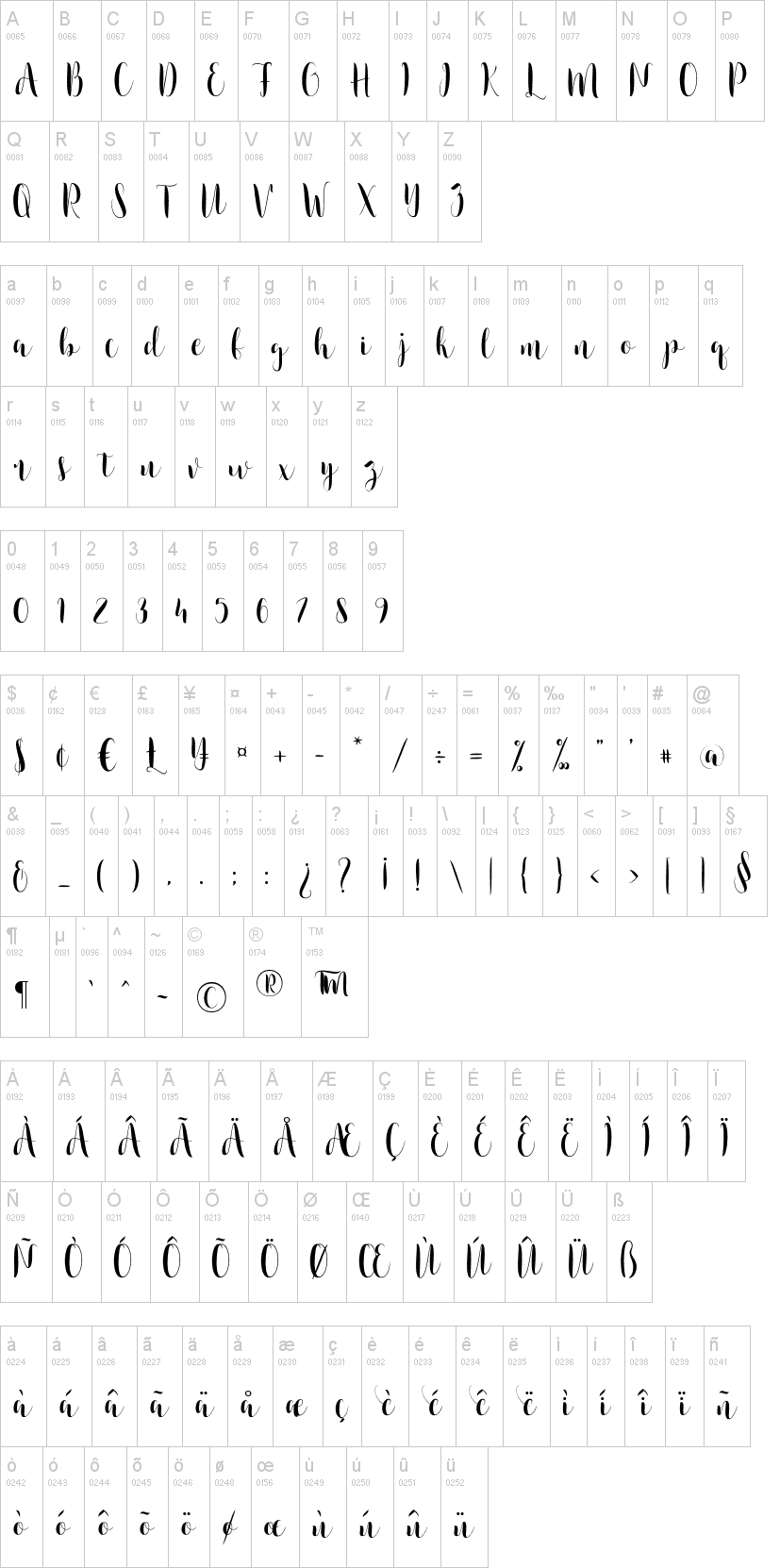
Camsia 字体是一款由 Fontfabric 公司推出的英文字体,它采用现代外观设计,拥有多种文字风格,可以满足不同设计需求。它拥有非常棒的设计感,可以提供清晰的文字效果,适用于多种文档类型,包括标题、正文、图片等等。它还有一个特殊的特点:它可以自动根据字体尺寸调整文字间距,以达到最佳的文字显示效果。内容介绍
Camsia是一款非常不错的手写艺术字体,具有很好的视觉感,适合于文化类的宣传设计、商业类品牌的广告和产品包装设计以及个性化文字排版等较多场景。